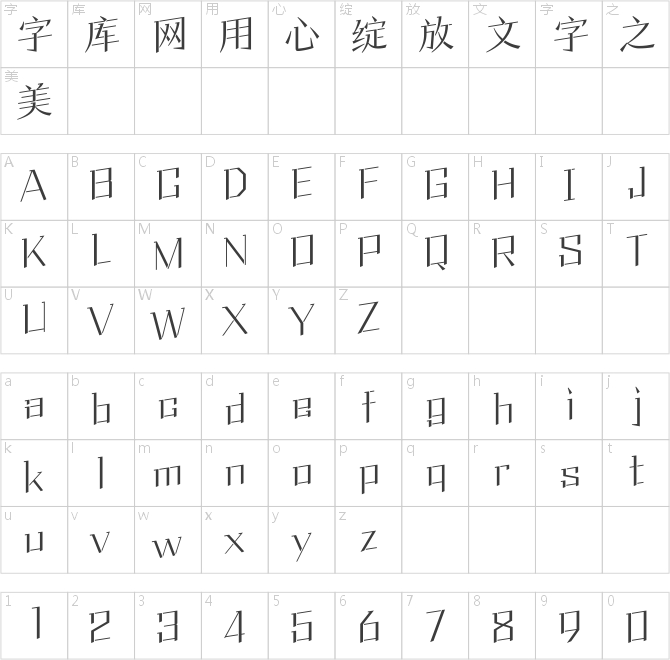
字体名称: 方正风入松体
方正风入松体
方正风入松体介绍
风入松体是宋体字的传承与进化,文字笔画的衔接和交叉处给人的视觉反应就是堆墨,镂空的方式本身就很有趣,让这款字体白区贯通,更加透气,象风入松一样高雅灵动,9度的右上倾斜,提振精神,感觉很爽!该字体的应用更侧重于标题字,也许能够起到画龙点睛的作用。